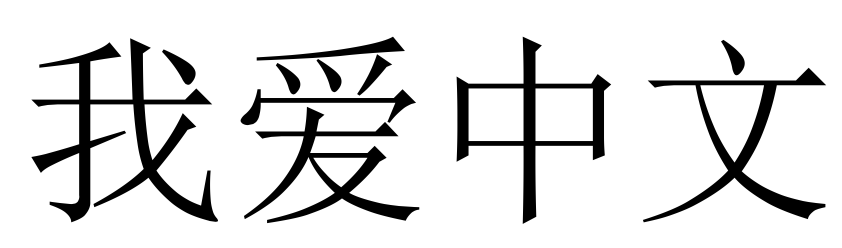
Designer thiết kế bao bì xuất khẩu sang thị trường Trung Quốc thường gặp lỗi font tiếng Trung bị thiếu ký tự Hán tự, mất dấu Pinyin hoặc hiển thị sai khi chuyển file sang hệ thống in công nghiệp. Những lỗi này có thể làm sai lệch thông tin sản phẩm, khiến bao bì thiếu tính chuyên nghiệp và gây khó khăn cho người tiêu dùng trong quá trình tiếp nhận nội dung.
Xưởng In Viva cung cấp bộ tải font tiếng Trung với khả năng hỗ trợ ký tự Trung Quốc đầy đủ, giúp doanh nghiệp thiết kế và sản xuất bao bì, tem nhãn cùng các dòng quà tặng đối ngoại đạt độ sắc nét cao.
Font chữ tiếng Trung giản thể là gì?
Font chữ tiếng Trung giản thể (Simplified Chinese) là hệ thống ký tự được chuẩn hóa và tối giản số nét vẽ từ chữ Hán truyền thống, hiện đang là ngôn ngữ chính thức tại Trung Quốc đại lục, Singapore và Malaysia. So với chữ Phồn thể, chữ Giản thể có cấu trúc thoáng hơn, giúp việc đọc trên các màn hình điện tử và in ấn trên các bao bì kích thước nhỏ trở nên dễ dàng hơn. Trong ngành thiết kế, việc lựa chọn đúng phông chữ Giản thể không chỉ đảm bảo tính chính xác về mặt ngôn ngữ mà còn thể hiện sự am hiểu văn hóa đối với thị trường tỷ dân.
Bên cạnh đó, nhu cầu tải font tiếng trung có pinyin cũng tăng cao trong các dự án thiết kế giáo trình, sách hướng dẫn sử dụng sản phẩm hoặc bao bì dành cho đối tượng học tiếng Trung. Pinyin (Phiên âm) giúp người đọc dễ dàng phát âm chính xác các ký tự khó. Tuy nhiên, các bộ font tích hợp sẵn pinyin thường rất nặng và dễ lỗi bảng mã nếu không được tối ưu kỹ thuật. Bộ font mà In Viva chia sẻ đã được chọn lọc từ những thư viện uy tín, đảm bảo hiển thị đồng bộ cả ký tự Hán và thanh điệu pinyin một cách thẩm mỹ.
Lưu ý: Khi bạn thực hiện thiết kế cho thị trường Trung Quốc đại lục, hãy ưu tiên tải font tiếng trung giản thể. Việc dùng nhầm font Phồn thể (Traditional) cho khách hàng đại lục có thể bị coi là thiếu chuyên nghiệp trong quy chuẩn giao thương.
5 ứng dụng của font tiếng Trung chuẩn trong thiết kế và in ấn
Khả năng hỗ trợ đầy đủ ký tự Hán tự giúp font tiếng Trung trở thành lựa chọn phù hợp cho các dự án bao bì xuất khẩu, quà tặng đối ngoại và các ấn phẩm thương hiệu hướng đến khách hàng Trung Quốc:
- Thiết kế bao bì nông sản xuất khẩu: Font tiếng Trung chuẩn được sử dụng để thể hiện tên sản phẩm, thành phần, hướng dẫn sử dụng và thông tin chứng nhận trên hộp giấy Ivory đựng thanh long, sầu riêng, hạt điều hoặc các sản phẩm đặc sản Việt Nam. Việc lựa chọn đúng bộ font giúp nội dung hiển thị rõ ràng, hạn chế lỗi sai ký tự khi in số lượng lớn.
- Sản xuất quà tặng doanh nghiệp in logo đối ngoại: In Viva ứng dụng font tiếng Trung trong các sản phẩm như bình giữ nhiệt, sổ tay, bộ ấm chén gốm sứ hoặc hộp quà tặng dành cho đối tác Trung Quốc. Các câu chúc, tên thương hiệu hoặc thông điệp tri ân bằng chữ Hán khi kết hợp cùng kỹ thuật in UV, khắc laser hoặc in nung giúp món quà trở nên trang trọng hơn.
- In ấn Catalogue và Profile song ngữ Việt – Trung: Font tiếng Trung hỗ trợ doanh nghiệp trình bày thông tin giới thiệu sản phẩm, năng lực sản xuất và hồ sơ thương hiệu trong các tài liệu xúc tiến thương mại. Bố cục song ngữ được trình bày rõ ràng giúp khách hàng dễ dàng tiếp nhận thông tin khi tham gia hội chợ, triển lãm quốc tế.
- Trang trí biển hiệu và thực đơn nhà hàng: Các bộ font tiếng Trung từ phong cách hiện đại đến thư pháp có thể ứng dụng trong thiết kế bảng hiệu, menu, poster hoặc vật phẩm trang trí dành cho nhà hàng, khách sạn phục vụ khách hàng người Hoa.
- Gia công tem nhãn decal cho hàng hóa xuất khẩu: Font tiếng Trung được sử dụng để in tên sản phẩm, mã hàng, hướng dẫn bảo quản và thông tin nhận diện trên tem nhãn. Ký tự rõ nét giúp doanh nghiệp kiểm soát tốt nội dung bao bì trong quá trình vận chuyển và phân phối hàng hóa.
5 lưu ý khi sử dụng font chữ tiếng Trung trong thiết kế và in ấn
Do đặc điểm của hệ thống chữ tượng hình với nhiều nét phức tạp, designer cần chú ý các yếu tố kỹ thuật sau để đảm bảo chất lượng thành phẩm:
- Kiểm tra bộ ký tự Hán tự trước khi thiết kế: Không phải mọi font tiếng Trung đều hỗ trợ đầy đủ chữ Giản thể hoặc Phồn thể. Trước khi sử dụng, designer nên kiểm tra các ký tự đặc biệt trong tên thương hiệu, địa danh hoặc thông tin sản phẩm để tránh lỗi thiếu chữ khi xuất file.
- Tối ưu đường Path cho gia công bế nổi: Khi sử dụng chữ Trung Quốc để dập nổi logo hoặc ép kim trên hộp quà cao cấp, file thiết kế cần được chuyển đổi sang vector và xử lý các chi tiết nhỏ. Việc này giúp khuôn gia công thể hiện chính xác từng nét chữ, hạn chế tình trạng mất nét hoặc biến dạng trên bề mặt giấy.
3. In Viva có hỗ trợ thiết kế bao bì sử dụng font tiếng Trung không?
Có. Đội ngũ In Viva hỗ trợ tư vấn bố cục, chất liệu và kỹ thuật gia công phù hợp cho các mẫu bao bì, tem nhãn và quà tặng có nội dung tiếng Trung hoặc song ngữ.